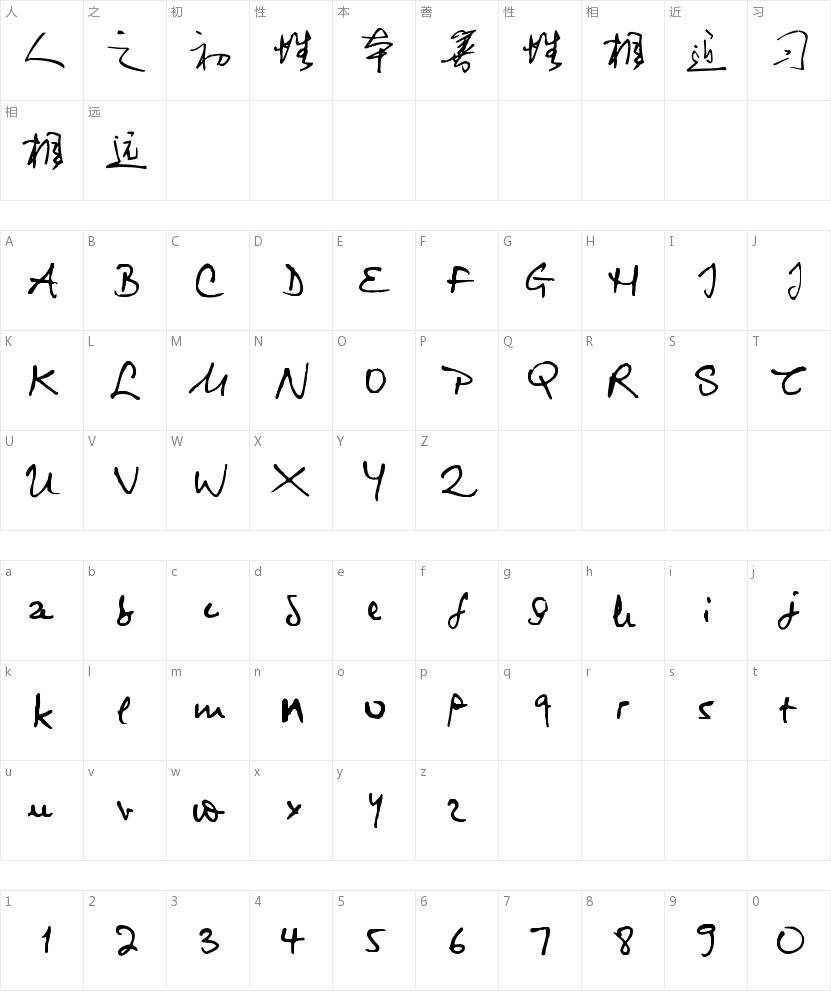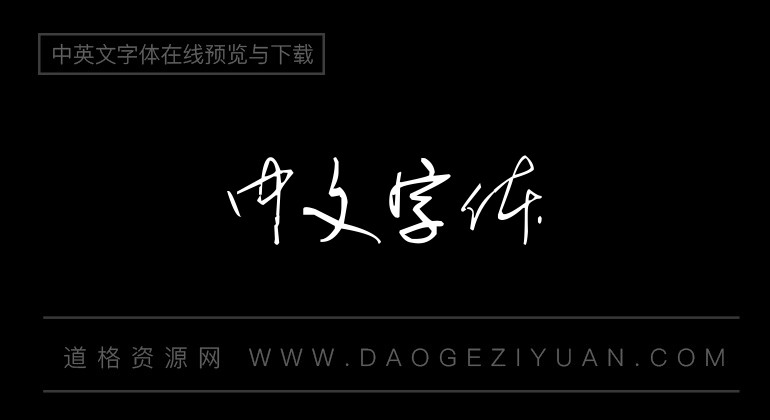
方圆疾风草书
方圆疾风草书是一款简洁大气的行书字体,设计师以古典楷书为基础,以现代技术优化技术,结合现代设计概念,结合折衷的风格,打造出一款具有古典气息的行书字体。字体的笔画细腻,曲线优美,笔画流畅,笔画宽度均匀,笔画自然,字体的格式兼容性强,可以在各种编辑软件中使用,可以满足不同的应用需求。
方圆疾风草书是一款非常不错的手写艺术字体,具有很好的视觉感,适合于文化类的宣传设计、商业类品牌的广告和产品包装设计以及个性化文字排版等较多场景。